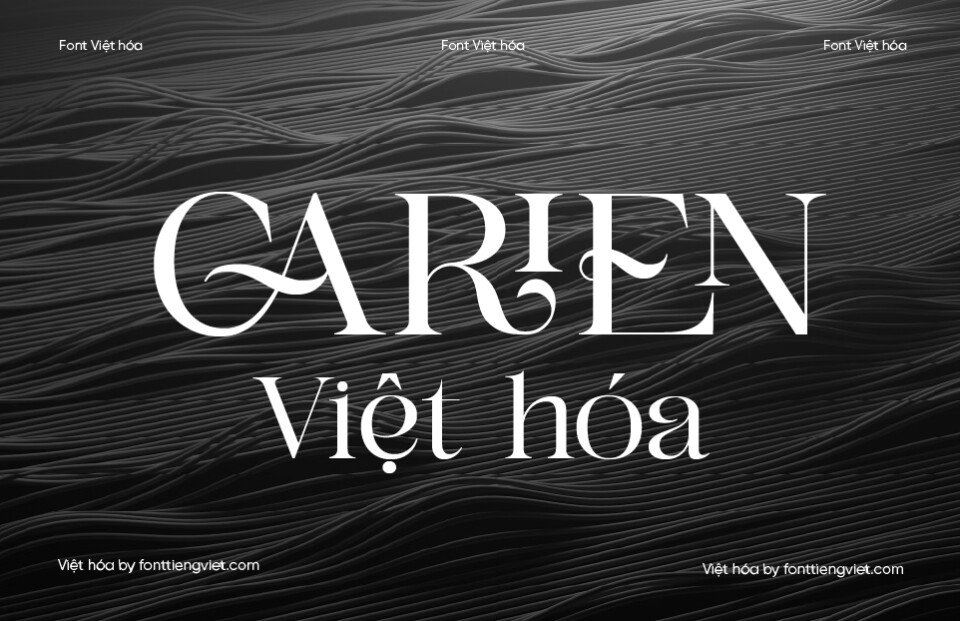
Giới thiệu về Font Việt hóa 1FTV VIP Carien
Trong môi trường học đường hiện nay, việc lựa chọn một Font Chữ phù hợp đóng vai trò quan trọng trong việc truyền tải kiến thức. Font Việt hóa 1FTV VIP Carien là một bộ phông chữ hiện đại, được tối ưu hóa hoàn toàn cho tiếng Việt với đầy đủ các dấu thanh chuẩn xác. Với đường nét thanh mảnh nhưng vô cùng chắc chắn, bộ font này mang lại cảm giác chuyên nghiệp, giúp các bài giảng và tài liệu học tập trở nên sinh động hơn. Đây là lựa chọn lý tưởng cho các thầy cô giáo và học sinh muốn tạo ra những sản phẩm sáng tạo, từ bài thuyết trình đến báo tường hay các ấn phẩm trang trí lớp học.
Đặc điểm nổi bật của Font Việt hóa 1FTV VIP Carien
Tính ứng dụng cao trong giảng dạy
Font Việt hóa 1FTV VIP Carien sở hữu thiết kế tinh tế, dễ đọc, giúp học sinh không bị mỏi mắt khi theo dõi nội dung dài. Khả năng hiển thị tốt trên cả màn hình máy tính và bản in giúp các tài liệu giáo dục luôn giữ được sự đồng nhất và tính thẩm mỹ cao.
Hỗ trợ tiếng Việt hoàn hảo
Điểm mạnh nhất của Font Việt hóa 1FTV VIP Carien chính là bộ ký tự tiếng Việt được tinh chỉnh tỉ mỉ. Các dấu câu không bị đè lên chữ, đảm bảo tính đúng đắn của ngôn ngữ, hỗ trợ đắc lực cho việc soạn thảo văn bản quy chuẩn trong nhà trường.
Cách sử dụng và kết luận
Để tận dụng tối đa vẻ đẹp của bộ font này, người dùng nên kết hợp với các tông màu trung tính hoặc pastel để tạo sự hài hòa. Việc cài đặt rất đơn giản, chỉ cần vài thao tác là bạn đã có thể sở hữu một công cụ thiết kế tuyệt vời. Hy vọng bộ Font Miễn Phí, Font Việt Hóa, Font Việt hóa 1FTV VIP Carien này sẽ giúp ích cho cộng đồng giáo dục trong việc nâng cao chất lượng thẩm mỹ của các dự án sáng tạo. Hãy tải ngay để trải nghiệm sự khác biệt trong từng nét chữ.